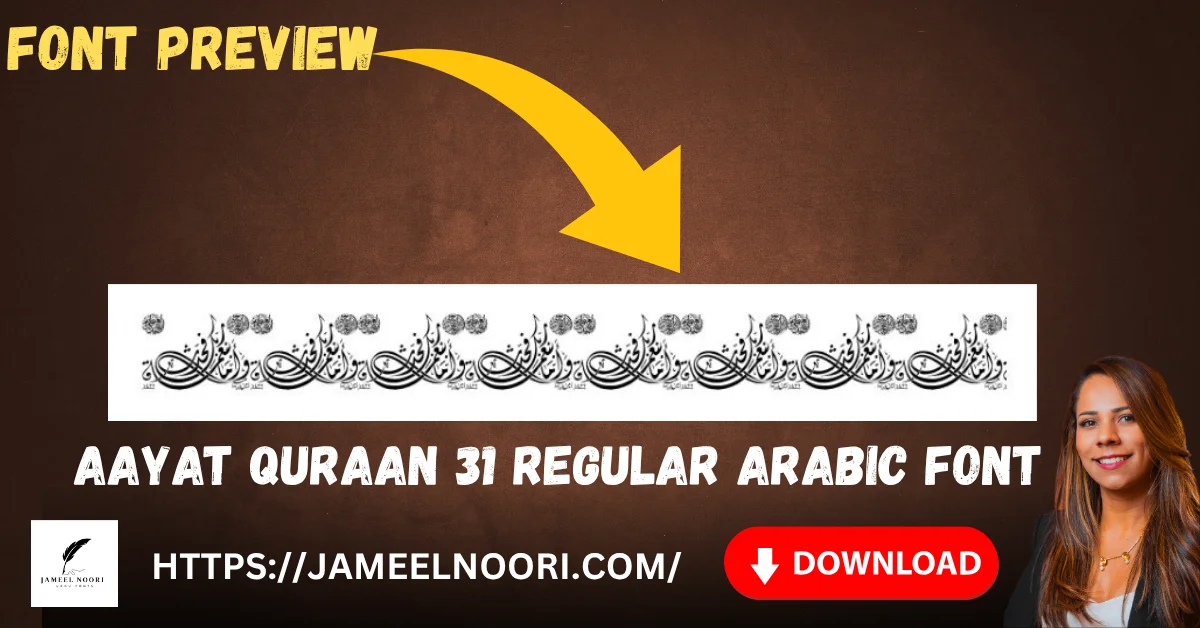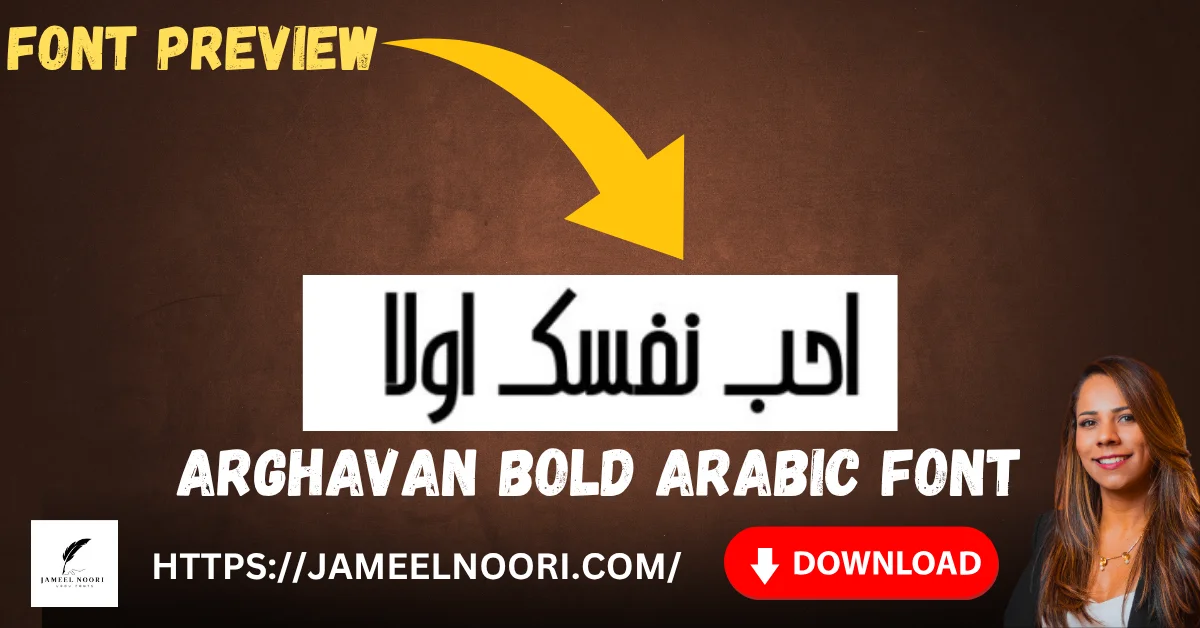
Aayat Quraan 12 Regular Arabic Font – Beautiful Font
Aayat Quraan 12 Regular Arabic Font - Beautiful Arabic Calligraphy
ayat Quraan 12 Regular Arabic Font is a beautiful and highly versatile TrueType font widely appreciated by designers, publishers, and Islamic scholars across Pakistan. This font is perfect for creating authentic Arabic text, Quranic verses, and other religious or educational content.
Aayat Quraan 21 Regular Arabic Font – Most Popular & Beautiful Arabic Calligraphy Font
The Aayat Quraan 21 Regular Arabic Font is one of the most popular and beautiful Arabic calligraphy fonts used across Pakistan for Quranic text, Urdu projects, and Islamic designs. This font is a Regular TrueType Font downloaded more than 13,934 times, with 172 users rating it 4.53 out of 5.
Aayat Quraan 53 Regular Arabic Font: Complete Guide for Arabic Users
Aayat Quraan 53 Regular Arabic Font – Beautiful Calligraphy Example
Aayat Quraan 53 Regular Arabic Font ek high-quality Regular TrueType font hai jo Urdu aur Arabic fonts ke shaukeen users ke liye perfect hai. Is font ko ab tak 66,584 martaba download kiya ja chuka hai aur 341 users ne 5.0 out of 5 rating di hai.
Aayat Quraan 31 Regular Arabic Font – Best Choice for Arabic Writing
Aayat Quraan 31 Regular Arabic Font aik bohot mashhoor aur high-quality Arabic writing font hai jo specially designers, students, aur Islamic content creators ke liye perfect samjha jata hai.
Arghavan Bold Arabic Font example showing elegant bold calligraphy
Arghavan Bold Arabic Font ek modern aur stylish bold TrueType font hai jo designers aur calligraphy lovers ke liye perfect choice hai.